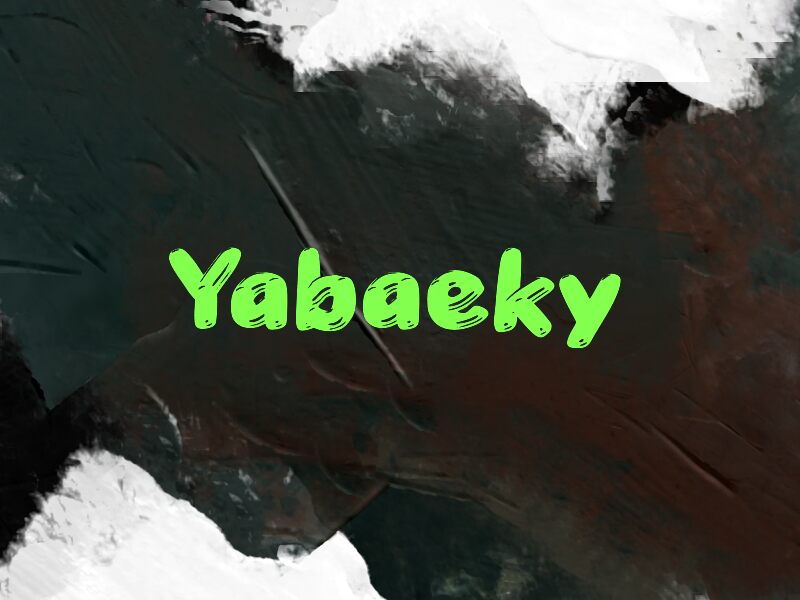
Yabaeky
Yabaeky da Wep é uma fonte de pincel gratuita composta por formas volumosas, carregadas de tinta e estrias brancas nítidas que imitam o arrasto de um pincel húmido sobre a superfície. Essa textura brilhante e densa confere às letras um toque cartoon pintado à mão, assemelhando-se mais a uma pintura fresca de letreiros do que a uma escrita limpa de marcador.
Cartazes, gráficos para streamers, embalagens, capas de álbuns e cabeçalhos de redes sociais combinam perfeitamente com este estilo, especialmente quando um título precisa de uma presença marcante e pictórica sem parecer áspero. A massa arredondada e os cortes de brilho tornam a Yabaeky ideal para linhas de branding, nomes de eventos e miniaturas onde um efeito de pincel dinâmico e impactante é o objetivo.